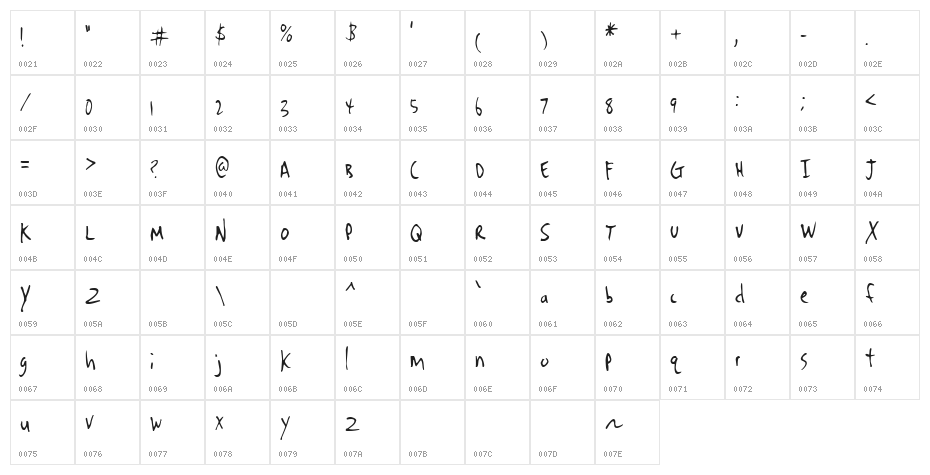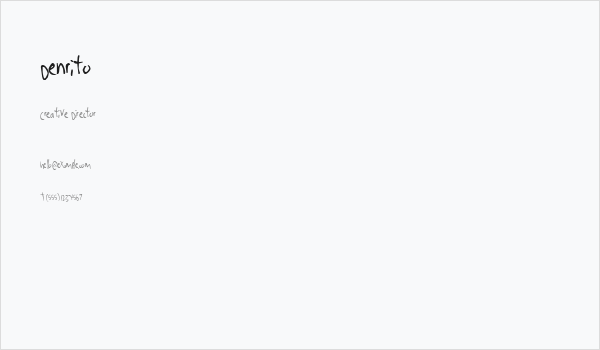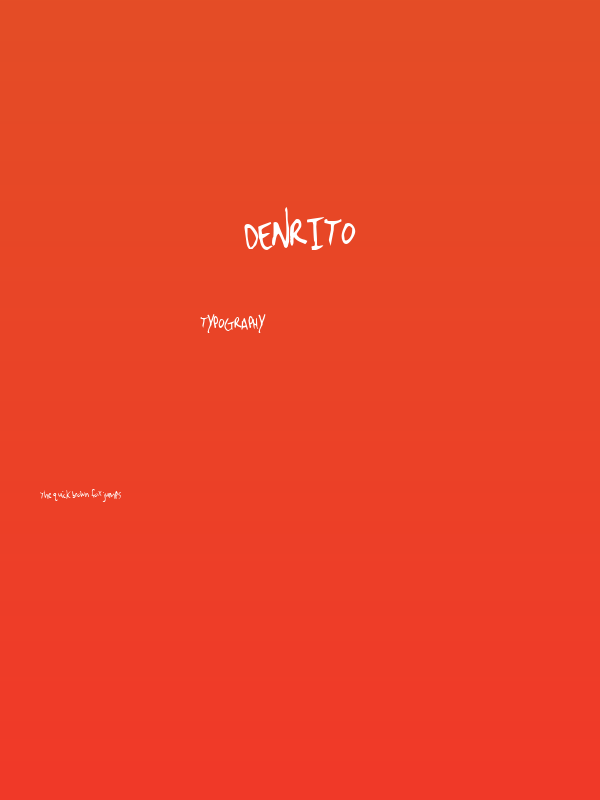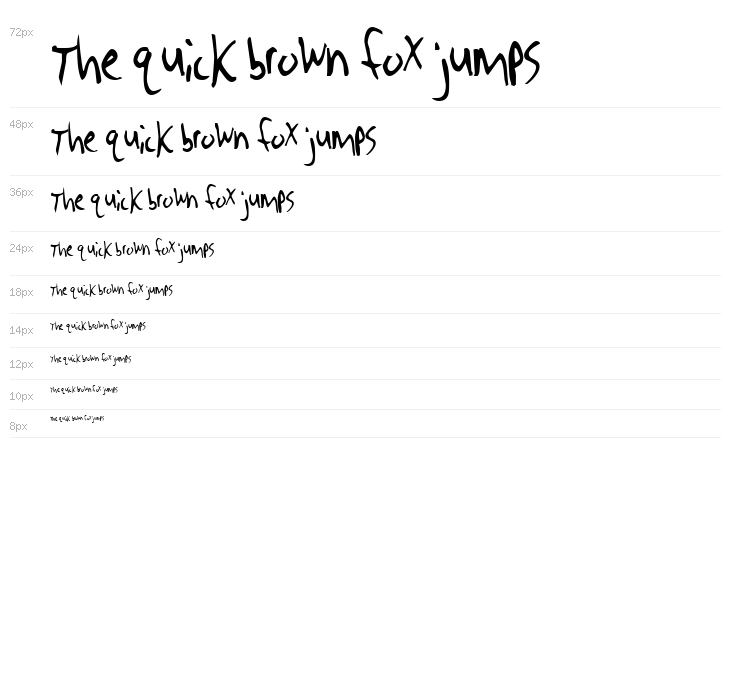
Denrito Font
| Gesamtstil | Casual |
| Anwendungsfall | Logos, Headlines, Informal text |
| Vorgeschlagene Projekte | Ideal for greeting cards, personal branding, social media graphics, and informal invitations. |